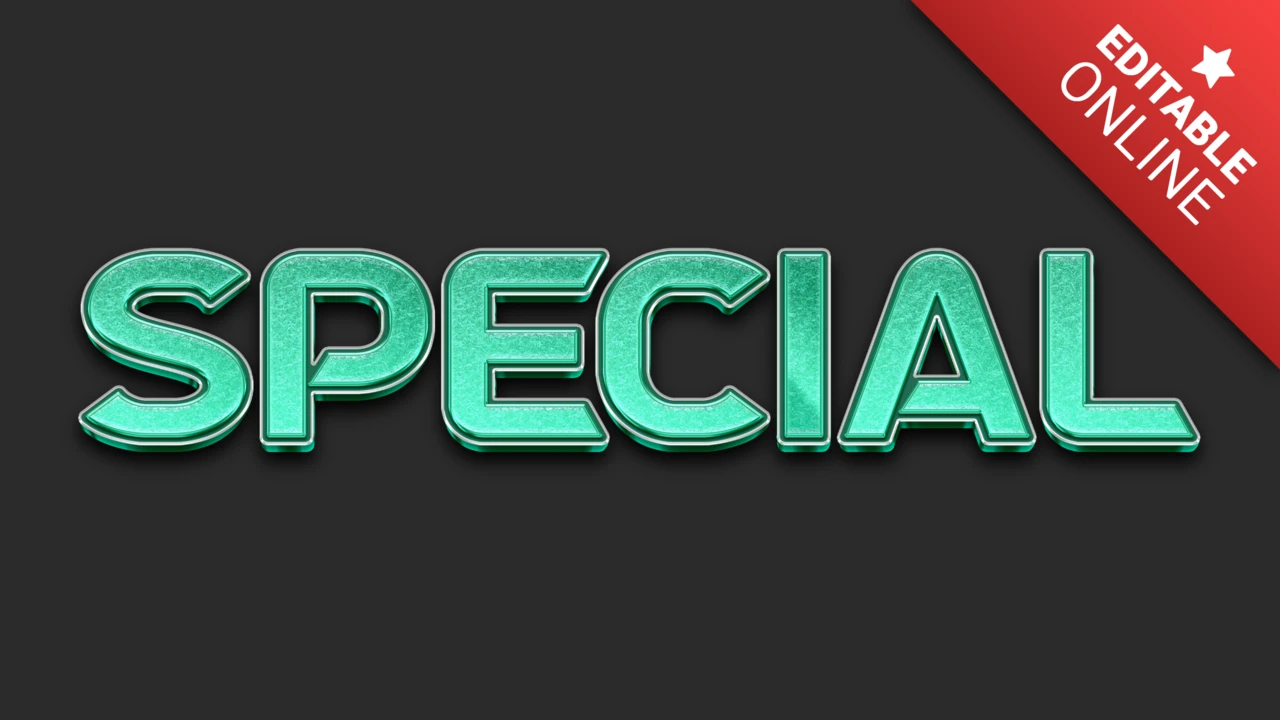
Effet de texte vert brillant - typographie 3d audacieuse
Libérez l'énergie vibrante de vos mots grâce à notre nouvel effet de texte qui transforme n'importe quel texte en une typographie 3D audacieuse avec une finition verte brillante et élégante. parfait pour faire une déclaration !